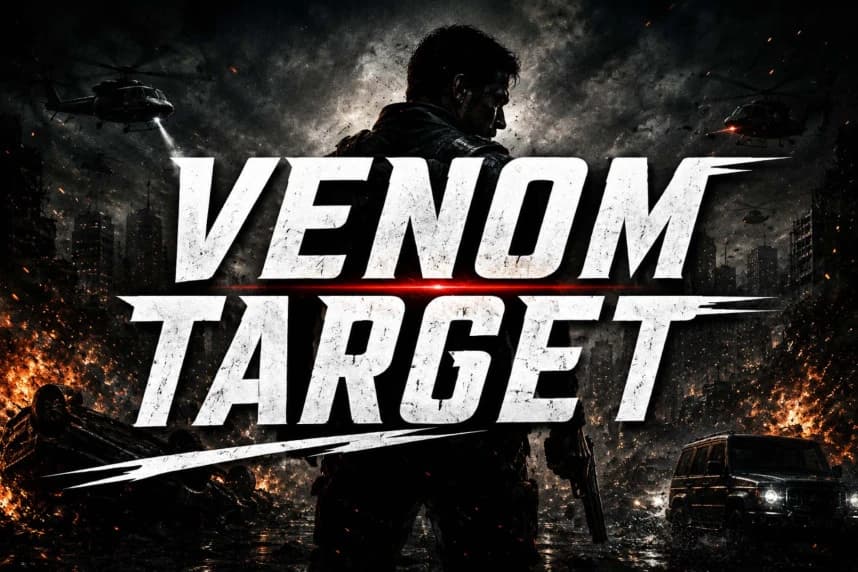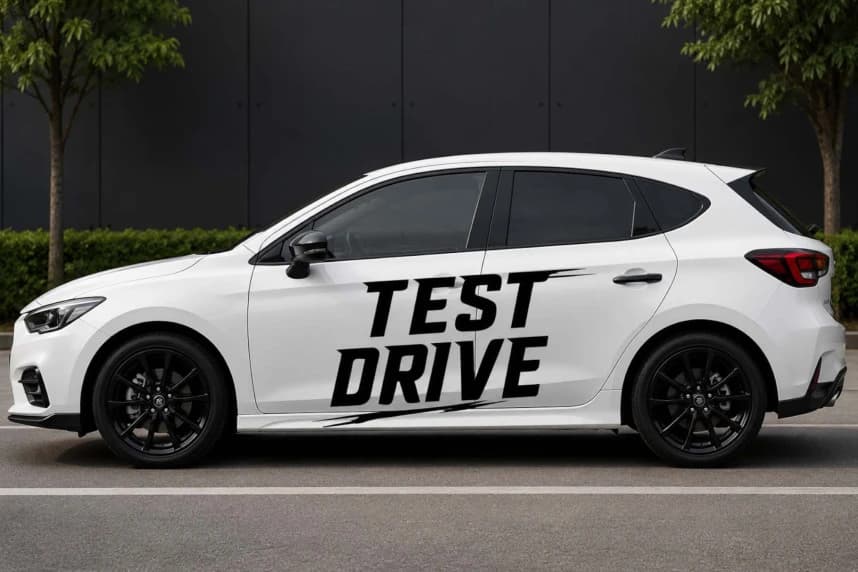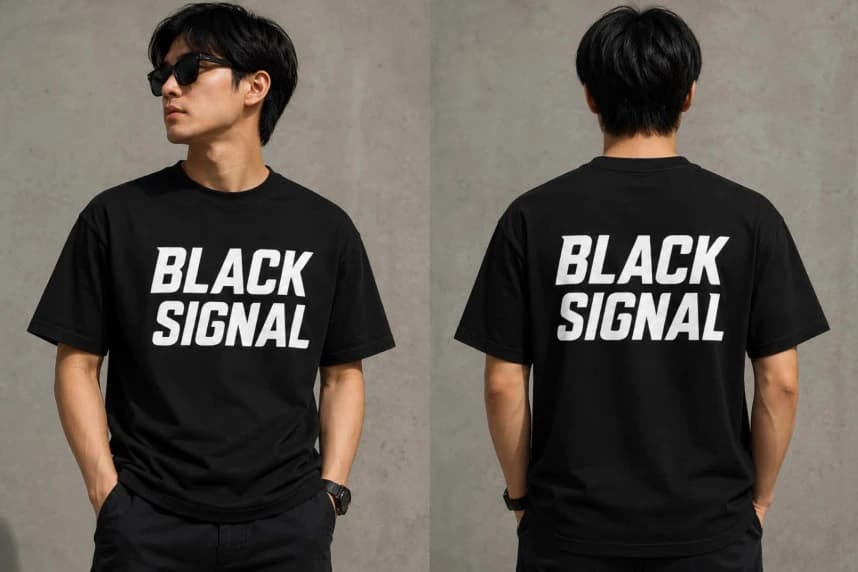
Morgan Strike Font
Morgan Strike Font, modern ve premium bir blackletter yazıtipidir. Bu yazıtipinin güçlü bir karakteri, hızlı bir hissi, kalın ve kendinden emin bir duruşu vardır. İki stili vardır: regular ve italic; alternates, swashes, büyük harfler, küçük harfler ve rakamlar ile donatılmış.
Morgan Strike Font modern ve premium bir blackletter yazı tipidir. Bu yazı tipi güçlü bir karaktere, hızlı bir hissi ve kendinden emin bir görünüm sunar. İki stili vardır: regular ve italic; alternatlar, swashes, büyük harfler, küçük harfler ve rakamlar ile donatılmıştır.